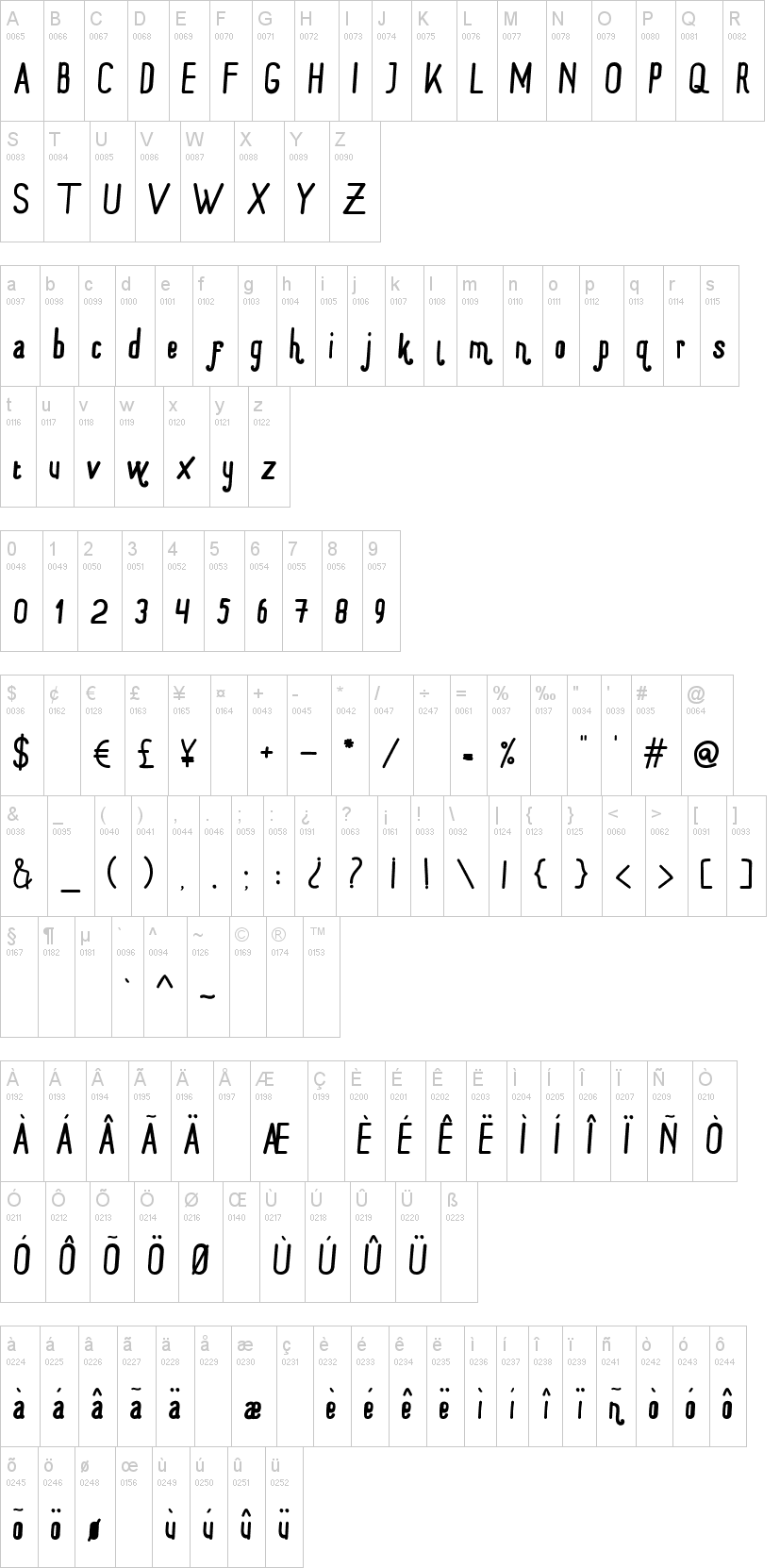
Moons 字体是一款由瑞典设计师 Mattias Nihlén 创作的一款具有独特风格的字体。它采用具有粗犷线条的设计,具有现代感,但又不失传统气息。Moons 字体拥有丰富的字形,可以满足各种设计需求,可以用于品牌标识、海报、T恤、印刷品等等。Moons 字体的特点是拥有简洁、清新、现代风格,可以为设计师提供更多的创作灵感。内容介绍
Moons是一款非常不错的手写艺术字体,具有很好的视觉感,适合于文化类的宣传设计、商业类品牌的广告和产品包装设计以及个性化文字排版等较多场景。